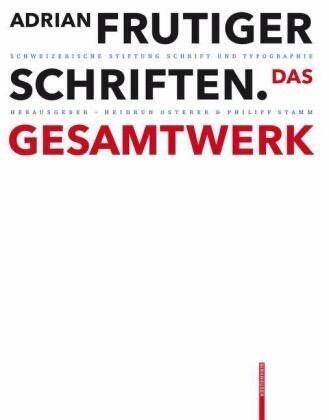
»Das internationale Schriftschaffen nach 1950 wurde massgeblich geprägt vom Schweizer Adrian Frutiger. Sein Schriftprogramm Univers und die zum ISO-Standard erklärte maschinenlesbare Schrift OCR-B sind Meilensteine wie auch die zur Frutiger weiterentwickelte Schrift der Pariser Flughäfen ein Qualitätsstandard für Signalisationsschriften. Mit den Corporate Types prägte er Firmenauftritte wie jenen der japanischen Kosmetiklinie Shiseido. Insgesamt entstanden rund 50 Schriften, darunter Ondine, Méridien, Avenir, Vectora.
Auf Gesprächen mit Frutiger basierend sowie auf umfangreichen Recherchen in Frankreich, England, Deutschland und der Schweiz zeichnet die Publikation den gestalterischen Werdegang des Schriftkünstlers exakt nach. Erstmals werden alle Schriften vom Entwurf bis zur Vermarktung abgebildet sowie mit Bezug zu Technik und zu artverwandten Schriften analysiert. Bisher unveröffentlichte, nicht realisierte Schriften sowie über 100 Logos vervollständigen das Bild.«
Wie mit dem Nagel festgehalten
Schriften in unserer Zeit: Ein großes, schweres, anregendes Buch über den Typographen Adrian Frutiger
von Martin Z. Schröder
Ist einem Schriftzeichner und seinem Beruf schon einmal eine derartige Aufmerksamkeit zuteil geworden? Es gibt eine recht kurze Reihe sehr schöner Bücher über Typografen und Schriftkünstler, etwa Ernst Schneidler, Jan Tschichold, Hermann Zapf; aber bislang gab es keines wie dieses über Adrian Frutiger, das Heidrun Osterer und Philipp Stamm herausgegeben haben. Es besteht nicht nur in einem Rückblick des Gebrauchsgrafikers und Schriftzeichners auf sein Lebenswerk, das uns täglich in Form seiner Schriften in Drucksachen und Ausschilderungen vor Augen steht, es ist nicht nur eine Sicht auf die schnellen weiten Sprünge der Drucktechnik vom Bleisatz zum Desktop Publishing binnen Jahrzehnten, nicht nur schriftgeschichtliche und -ästhetische Kritik, nicht bloß eine Sammlung von Schautafeln – es ist dies alles in einem! Und bildet so das umfassendste Werk über Schrift in unserer Zeit, das sich überhaupt denken läßt.
Nun hat es von der ersten Annäherung der Herausgeber an dieses über 2 Kilo schwere Werk, das man wegen seines Formates nur auf einem Tisch aufschlagen kann, zehn Jahre und etliche Reisen durch Schriftarchive und Bibliotheken in mehreren Ländern bis zur Veröffentlichung gebraucht, und ist für den Benutzer segensreich, daß sein 81jähriger Pate Adrian Frutiger bis zur Fertigstellung mitwirken konnte. Entstanden ist aus diesen Anstrengungen nicht nur eine enorme Arbeitsbiografie, auch die Bedeutung der Schrift an sich wird deutlich: Mit der Ausbreitung des gedruckten Wortes begann die Schrift zum gewöhnlichen Medium zu werden und wird ihr heute, nachdem man sie einmal zu lesen und halbwegs zu schreiben gelernt hat, kaum noch Aufmerksamkeit zuteil. Man bemerkt sie, wenn sie Anstoß erregt, etwa weil sie unleserlich ist oder weil sie sich propagandistisch aufdrängt. Adrian Frutiger nennt einen hübschen Vergleich, um zu zeigen, wie wichtig die Funktionalität im Design von Schrift als Medium des Geistes ist: „Schrift ist wie ein Löffel: wenn ich mich am Abend an die Form des Löffels erinnere, mit dem ich am Mittag meine Suppe gegessen habe, dann war es eine schlechte Löffelform.“ Die Lesbarkeit ist also der Schrift erste Funktion – aber sie transportiert schon seit ihrer Entstehung viel mehr, gerade wenn ihr der Zeichner seine individuellen Züge auszutreiben sucht. Sie bildet die Inneneinrichtung unserer Geisteswelt. In ihr selbst, ihrer Strichführung, ihrem Aufbau und in ihrer Anwendung durch die Typografie, also den Entwurf mit Lettern, steckt der Zeitgeist – und auch ihn kann man lesen – wie die Fassaden und das Interieur von Häusern nicht schweigen über ihre Bewohner. So wie sich in Gutenbergs gotischen Lettern ein Bild der Baukunst spiegelt, wie man darin den Zeitaufwand findet, den ein mit der sorgfältig zugeschnittenen Feder gezeichneter Buchstabe beansprucht, wie auch das dunkle, schmale Textgewebe hinweist auf die dem geschriebenen Wort zugewiesene feierliche Würde, so verraten andere Schriften andere Alltagskultur und Geisteshaltung. Auch die stets wiederkehrende Rückbesinnung gehört dazu: immer wieder neue Renaissancen. Aus diesen entstehen die bleibenden Werke, das klassische ist zugleich das menschlichste Werk, es wird über Jahrhunderte verstanden.
Zu jeder seiner Schriften erzählt Frutiger ihre Entstehungsgeschichte, die meist in einer Schriftgießerei begann, etwa bei Deberny & Peignot in Paris: Anfang der fünfziger Jahre arbeiteten dort noch etwa einhundert Schriftgießer, die von fünfzehn Graveuren die Stahlstempel erhielten, aus denen die Gußformen für Lettern entstanden. Die Firma lebte von der Kunst eines einzigen Schriftzeichners: Adrian Frutiger. In den fünfziger Jahren wird aber auch in den Fotosatz investiert. An dieser Stelle gibt das Buch einen gründlich recherchierten Überblick und informiert über die Anfänge dieser Technologie, die bis ins Jahr 1893 zurückreichen. 1953 entstanden Frutigers erste Zeichnungen für seine weltweit verbreitete Schrift Univers. Er erzählt von den schrifthistorischen Untersuchungen, die er für diese Arbeit vornahm, um sie zu einer allgemein gebräuchlichen Schrift zu machen, und wie er die Figuren und Strichstärken aus seinem Gefühl entwickelte, auch wenn sie mathematisch berechenbar erscheinen mögen. Die Univers wurde im Laufe der Jahre für alle Technologien der Satzherstellung nutzbar gemacht, zuerst 1957 für den Fotosatz, ein Jahr später als Bleischrift, über Jahrzehnte in Modifizierungen für elektronische Satzverfahren, und heute wird sie von drei Herstellern für den digitalen Satz angeboten.
Frutiger erzählt, wie er Schablonen für Buchstabenteile schneidet und mit Sandpapier bearbeitet, um die richtige Rundung für jede Figur zu finden. Er spricht über handwerkliche Details seiner Arbeit wie auch über Fragen des Urheberrechts. In diesem Werk wird kein Aspekt der Schriftkunst ausgelassen, und Frutiger ist so wahrheitsliebend und offenherzig, daß er auch frank und frei über Fehlschläge oder bis heute offene Fragen spricht, etwa warum ihm eine bestimmte Schrift nicht gelungen sei.
Um so mehr freut man sich als Leser, wenn Frutiger schließlich über seine beste Arbeit spricht und Sätze sagt wie: „Hier wird meine Persönlichkeit wie mit einem Nagel festgehalten. Ich bin stolz, daß ich die Avenir machen konnte.“ Als Adrian Frutiger die Schrift Avenir zu entwerfen begann, zehrte er aus einer vierzigjährigen Erfahrung mit Schrift. Er wollte einer mit Zirkel und Lineal konstruierten Schrift eine neue, humane Gestalt geben. Jeder Schriftzeichner kennt die Grenzen, die das menschliche Gesichtsfeld zieht: es ist horizontal weiter als vertikal – wir blicken eher zu den Seiten als in Höhe und Abgrund – anders als manches rundäugige Tier, das Gefahr von allen Seiten zu gewärtigen hat. Frutiger verringerte also im kreisrund angelegten Buchstaben O die horizontalen Linien. Wie er darauf kommt, welche Versuche er mit seinen Kreationen anstellt, wie fein und nur noch fühlbar, nicht mehr sichtbar manche seiner Eingriffe in die harte Geometrie sind, das erzählt uns Frutiger in diesem Buch.
Zu seinen wesentlichen Schriftschöpfungen ließ er sich über zwei Jahre lang befragen – und die daraus entstandenen Transkripte wurden von ihm selbst, den Interviewern und vier Lektoren kontrolliert und überarbeitet. So genau und so ausführlich ist nie zuvor über die Erschaffung von Schrift geschrieben worden.
Die Erzählung Frutigers hat man durch Originalzitate aus anderen Quellen des Schriftzeichners ergänzt und durch fachkundige Kommentare vervollständigt, an welche wiederum ein Fußnotenkonvolut angehängt wurde, dessen Detailgenauigkeit den Schriftinteressierten vor Freude Luftsprünge und aus Dankbarkeit Verneigungen machen läßt: es ist eine anregende Lektüre. Neben der deutschen Ausgabe erschienen auch eine englische und eine französische.